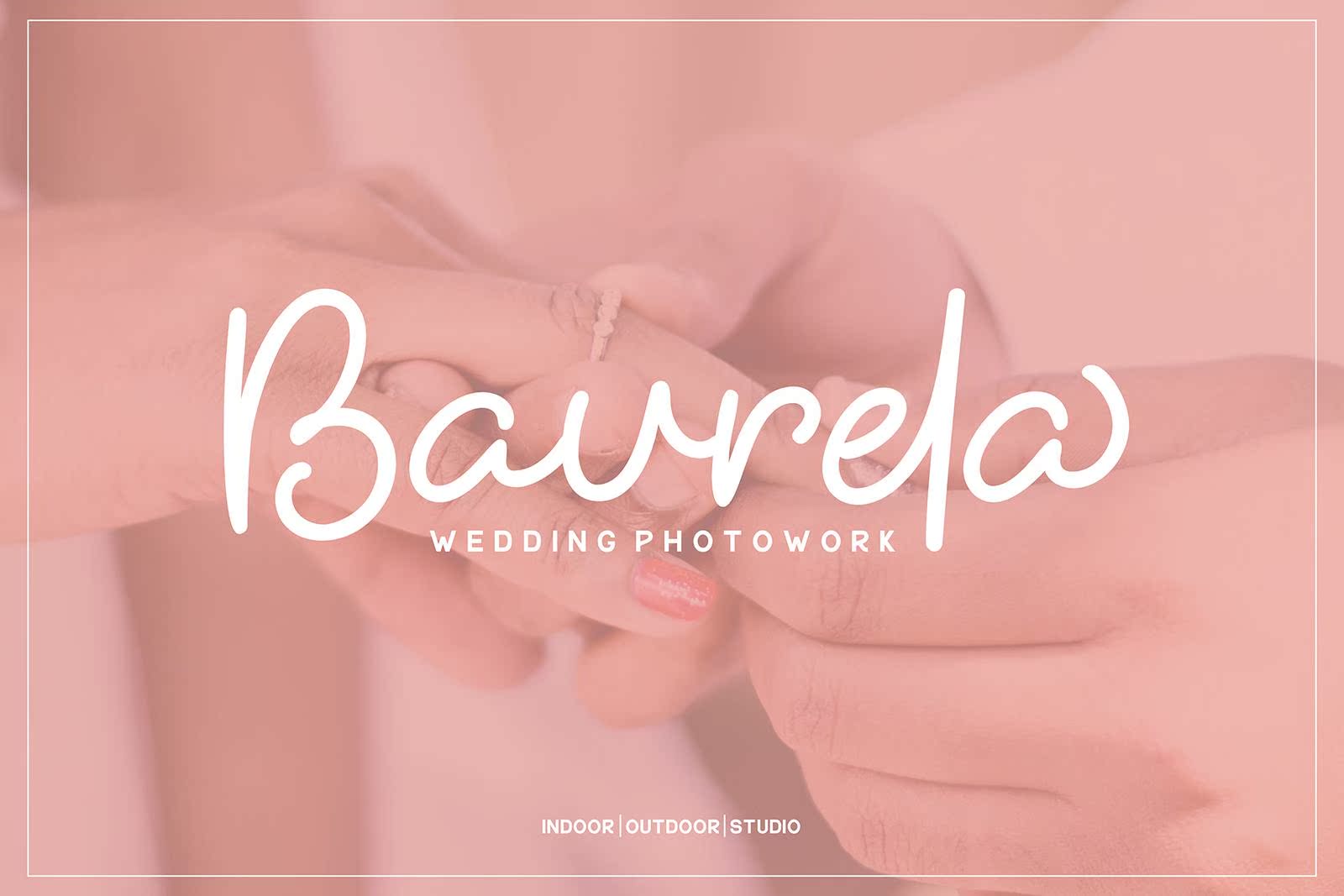
HiyaghAheyScript&Sans Font具有原始手写风格,外观自然美观。适用于精品品牌、摄影、杂志、报价、名片、徽标、Poster等。字体有两种类型:scriptandsans,Scriptisequipped,具有开放式功能,如纯正字体、连字、,上下文可选和多语言支持。HiyaghAheyScript&Sans字体具有原始手写样式,外观自然美观。适用于精品品牌、摄影、杂志、报价、名片、徽标、PosterAndMore。字体有两种类型:scriptandsans、Scriptisequipped,具有开放式功能,包括标准字体、连字和,上下文替换和多语言支持。